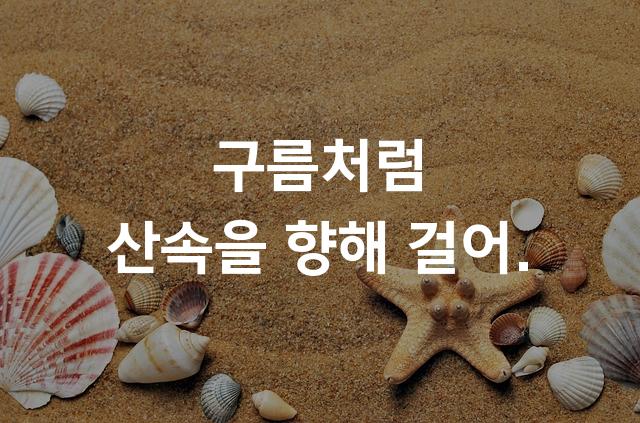
구름 산스 코드는 코딩을 위해 특별히 제작된 폰트로, 가독성과 편안함을 최우선으로 설계되었습니다. 개발자의 눈을 사로잡을 클린하고 모던한 디자인이 특징입니다.
구름 산스 코드은(는)
픽셀/코딩, 두꺼운 스타일, 감성적인, 자연감성, 부드러움, 복실복실 계열의 생김새를 가지고 있으며
웹/앱 디자인, 소셜 미디어, 보고서/문서 등에서 자주 활용되며, 효과적인 메시지 전달에 적합합니다.
이 폰트는 출판/미디어, 광고/마케팅, 기술/IT 분야에 잘 어울리며,
명확한, 전문적인, 단순한 느낌을 담고 있는 것이 특징입니다.